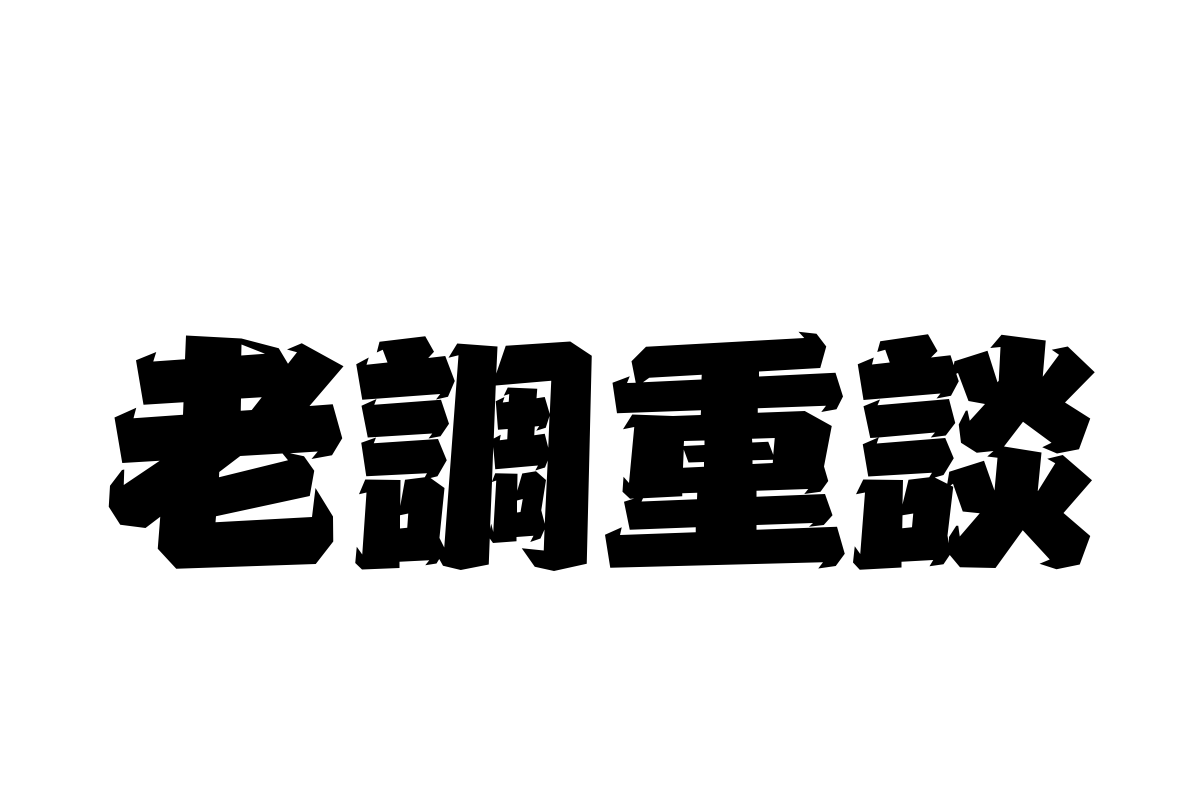
汉仪攀登者是一款具有独特风格的字体,其特点是笔画流畅、字形饱满且富有力量感。这款字体适用于各种需要展示力量和动感的设计场景,如广告设计、标志设计、包装设计等。
汉仪攀登者的特点在于其独特的笔画结构,使得每个字的形态都显得饱满而有力。这种特点使得汉仪攀登者在视觉上具有很强的冲击力,能够吸引人们的注意力。同时,由于其笔画流畅的特点,使得汉仪攀登者在阅读时也显得更加舒适。
总的来说,汉仪攀登者是一款非常适合用于需要展示力量和动感的设计的字体。无论是在广告设计还是标志设计中,都能展现出其独特的魅力。